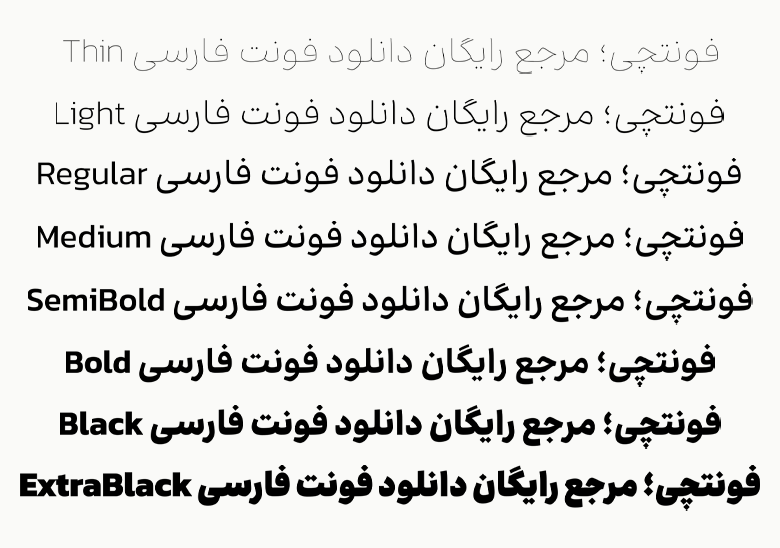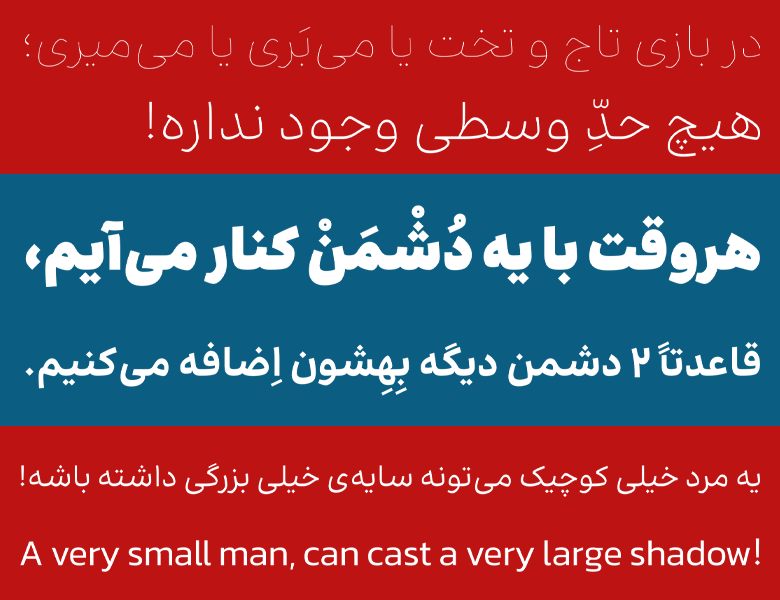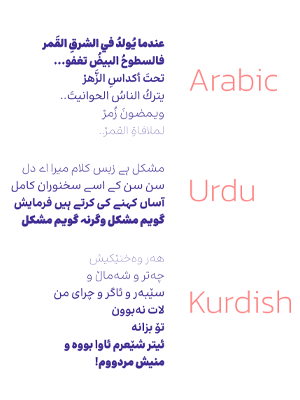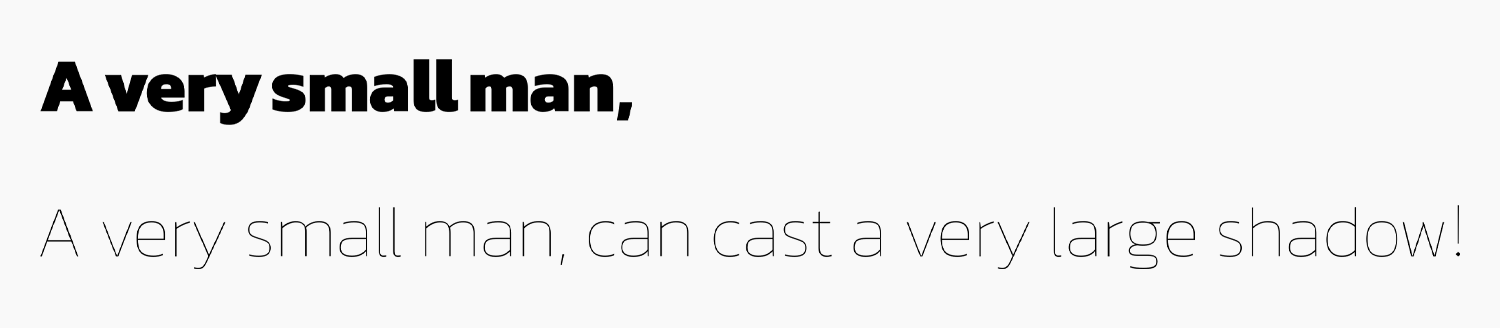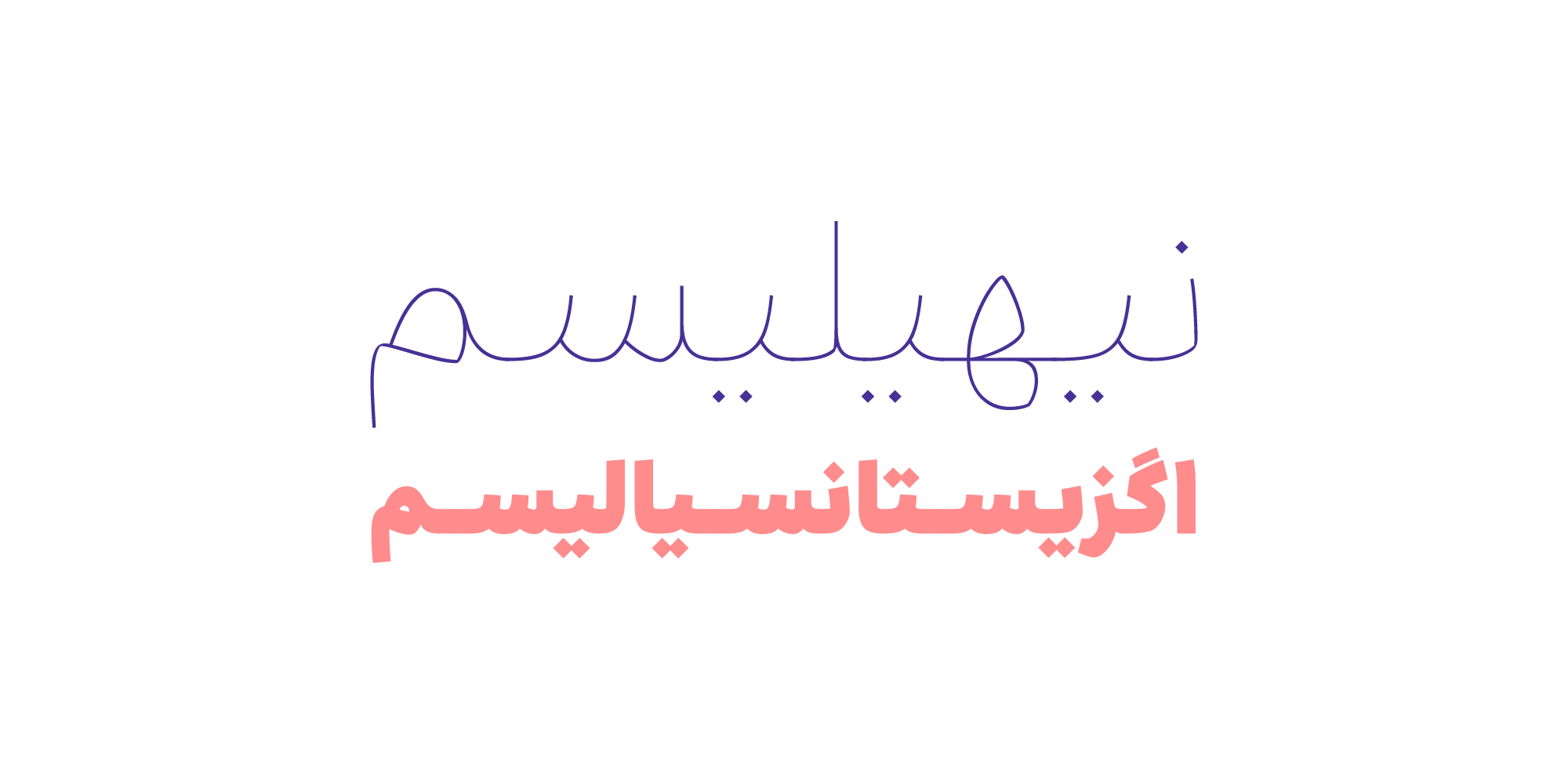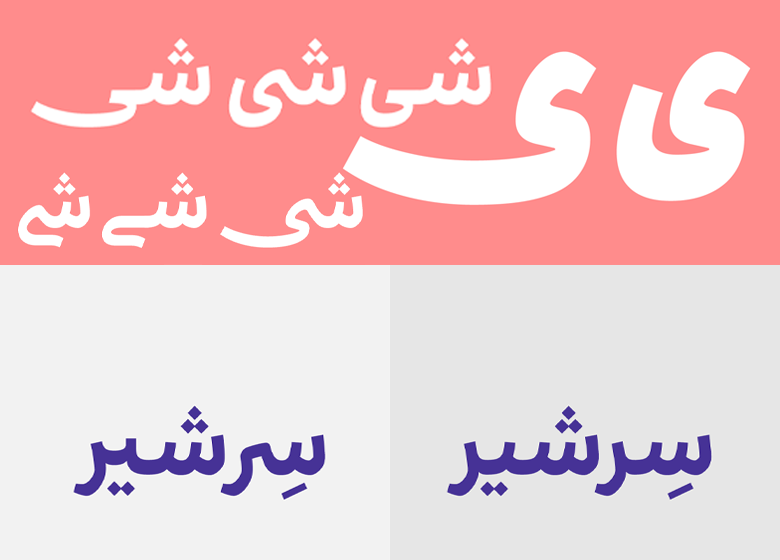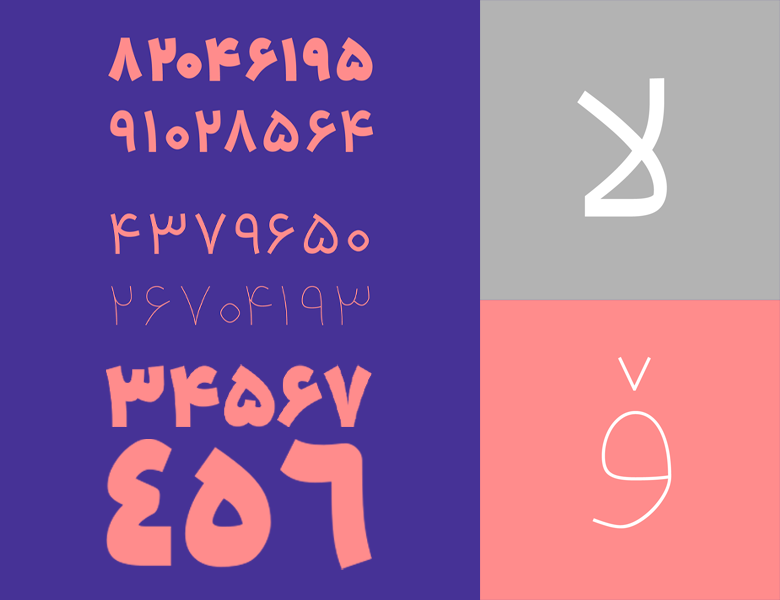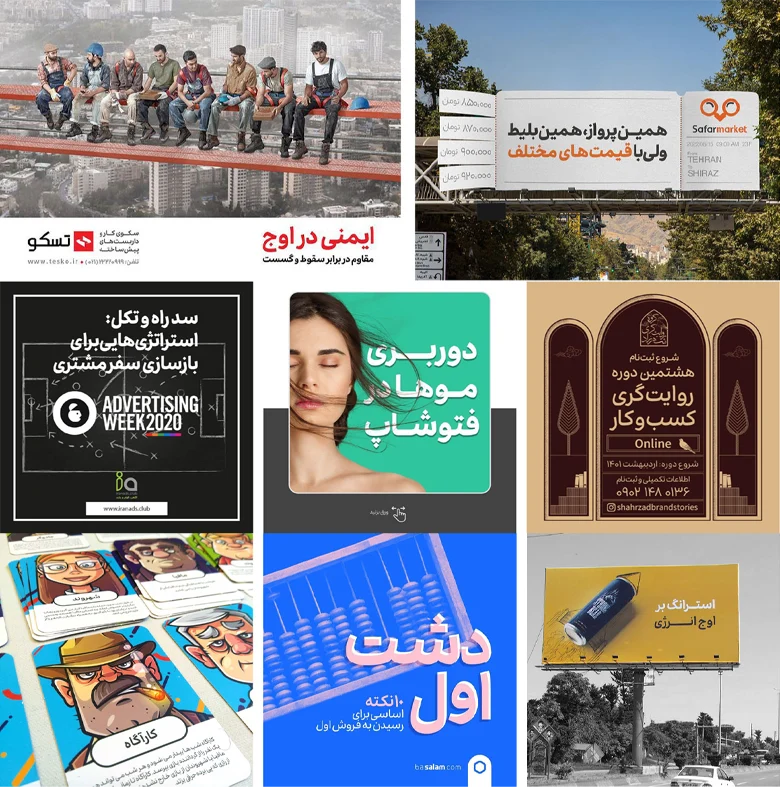
فونت راوی (Ravi)
فونت راوی (به انگلیسی: Ravi) با طراحی جسورانه، جوان و کاملا مدرنی که دارد سرشار از سرزندگی و شادابی است. این فونت با طنازی و شیطنتهای خاص خود که بر روی منحنیها و تقارن حروف قابل جایگزین دارد، میتواند نگاه کاربران را در شبکههای اجتماعی و تبلیغات محیطی دزدیده و متکلموحده شود. فونت راوی رایگان نیست و با تنوع وزنی و نسخه وریبل که دارد در ۳ بسته قابل خریداری است.
فونت راوی توسط رضا بختیاری فرد طراحی شده است و آنگونه که خود بیان داشته، «دغدغهام خوانایی و روانخوانی بود و بدون اغراق دهها بار در فضای چاپی و وب به روشها و در اندازههای مختلف آن را آزمایش و اصلاح کردم. پس با خیال راحت میتوانید در متنهای طولانیِ وبسایت و کاتالوگ و مجله از آن استفاده کنید».
این فونت سنس است و برای استفاده در متن طولانی انتخابی ایدهآل خواهد بود. جدایی از این برای استفاده در رابط کاربری و تبلیغات نیز با توجه به وزنهای مختلفی که دارد، میتواند انتخاب مناسبی باشد که در ادامه این نوشته از سایت فونتچی به نقد و بررسی کامل فونت راوی خواهیم پرداخت.
معرفی و بررسی فونت راوی (Ravi)
فونت Ravi دارای الفهای کوتاه، کاسههای کوچک و بدنهای منسجم است که هرسه این ویژگی برای طراحی UI انتخاب و رابط کاربری مناسب هستند. دندانههای بلند، چشمهای بزرگ و کنتراست بالا، در عینحال که ضخامت کمی از فونت را به نمایش میگذارد، اما همنشین خوبی برای حروف ایجاد کرده است که موجب افزایش خوانایی و جلب توجه بیشتر میشود.
سبک و وزن فونت راوی
تمامی ۸ وزن فونت راوی شامل Thin، Light، Regular، Medium، SemiBold، Bold، Black و ExtraBlack است که با توجه به تنوع و نزدیکی وزنهایی که هر نسخه به یکدیگر دارد، میتوان از آنها در قالب یک فونت خانوادهدار برای طراحی رابط کاربری سازمانی در قالب یک فونت یکپارچه استفاده کرد یا اینکه از وزنهای سنگین آن با هدف استفاده برای فونت عنوان، با یک فونت متن دیگر آن را ترکیب کرد.
ویژگی و مشخصات فونت Ravi
راوی یکی دیگر از بهترین فونتهای فارسی است که میتواند در هر محیطی نقش خود را بهخوبی ایفا کند. از محیطهای تبلیغاتی در فضای بیرون و دیجیتال که استفاده از ترکیبات جایگزین و وزنهای چاق و لاغر در اختیار قرار داده و کمک میکند طرحهای خلاقانه ایجاد کنید گرفته؛ تا محیطهایی برای متنهای طولانی همچون کتب، روزنامه و مطبوعات، وبسایت و اپلیکیشن که میتوان به شکل ترکیبی از وزنهای مختلف این فونت بهره برد.
اگر به دنبال دانلود فونت فارسی مناسبی هستید که خوانایی بالایی برای متون بلند داشته باشد، خانواده راوی یکی از قلمهای پیشنهادی است. شکل خاص این قلم در طراحی و چیدمان حروف از خستهشدن زود هنگام چشم جلوگیری کرده و کتابخوانی را با لذت هرچه تمامتر برایتان مهیا میکند.
پشتیبانی کامل از ۵ زبان مختلف
فونت راوی فارسی یکی دیگر از معدود فونتهایی است که محدود به این زبان نبوده و از سایر زبانهایی که بر اساس رسمخط فارسی هستند، همچون زبان کردی، عربی و اردو پشتیبانی کاملی دارد.
این پشتیبانی جدای از حروف که در همه این زبانها یکسان بوده و صرفا در برخی ترکیبات دارای تغییرات جزئی یا نسخه جایگزین است، محدود نیست و از اعراب، اعداد، کاراکترهای خاص، سمبلها و گلیفهای تزئینی هر زبان هم پشتیبانی کاملی دارد.
با دانلود فونت راوی برای فتوشاپ میتوانید از وزنهای ضخیم این قلم برای عناوین استفاده کنید که ظاهری نمایشی داشته و در جلب توجه مخاطبان خوب عمل میکند. این نوع وزن برای استفاده در فونت جلد عنوان کتاب میتواند انتخاب خوبی باشد.
در طراحی فونت Ravi انگلیسی از فونت اوپنسورس Kanit استفاده شده است که ارتباطی نزدیک با طراحی نسخههای فارسی دارد. در نتیجه لزومی ندارد که هنگام استفاده از این فونت به فکر یافتن فونت دیگری که نزدیک به این فونت باشد برای زبانهای لاتین بگردید.
فونت متغیر راوی با تغییر وزن
یکی دیگر از ویژگیهای بارز فونت راوی، متغیر بودن آن است. نسخه وریبل راوی این امکان را به شما خواهد داد که به جای نصب ۸ وزن مختلفی که این فونت دارد، همه وزنها را در قالب یک فایل فونت داشته باشید و از آنها در کلیه محیطهای نرمافزارهای گرافیکی، ویرایشگر متن و حتی وبسایت استفاده کنید.
چنین ساختاری جدا از اینکه روی بهبود و افزایش سرعت کاری شما تاثیر دارد، جدایی از این امکانات دیگری را نیز در اختیار شما قرار خواهد داد که به کمک متغیر وزن میتوانید وزن هر فونت را کنترل کنید.
همچنین با توجه به ساختارهای از پیش تعریف شدهای که در نسخه متغیر فونت راوی وجود دارد، بدون نیاز به استفاده از برنامه نویسی، کدهای JS و سایر راهکارهای موجود در فضای وب، میتوانید به سادگی با کمتر از ۵ خط CSS اعداد را به صورت تایپ فارسی داشته باشید.
دارای حروف و ترکیبات جایگزین
فونت راوی از ترکیبات جایگزین و حروف نیز پشتیبانی کاملی دارد که به شما این اجازه را خواهد داد در زبانهای مبتنی بر فارسی، امکان استفاده از یک حرف یا ترکیبات خاص آن را در چند شکل و ظاهر متفاوت داشته باشید.
به عنوان مثال همانطور که در تصویر زیر مشاهده میکنید، میتوانید حرف «ی» را در کلماتی که به این حرف ختم میشوند را در قالبهای متنوع زیر تایپ کنید.